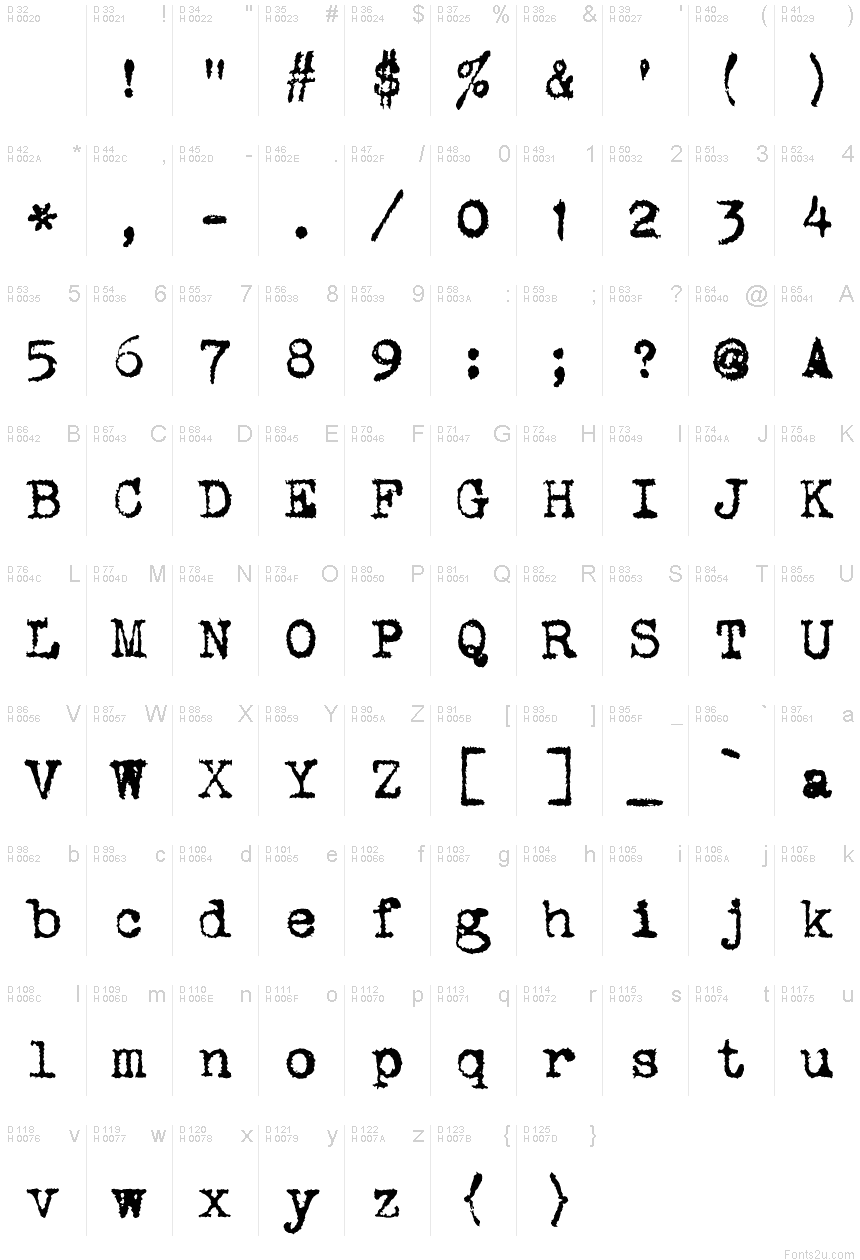
VTCorona
VT Corona, autorstwa Susan Townsend, to darmowy, surowy krój displayowy w stylu old-school, przywodzący na myśl klimat zużytych czcionek drukarskich i obitych drewnianych liter. Krawędzie znaków wyglądają na nadgryzione, a nierówne kontury i miękkie prześwity sprawiają, że projekt sprawia wrażenie autentycznie zniszczonego, a nie tylko sztucznie postarzonego.
Doskonale sprawdzi się na plakatach, nagłówkach w klimacie horroru, fanzinach, planszach tytułowych, etykietach barowych i ulotkach wydarzeń, gdzie darmowy font musi mieć charakter, ale nie może być zbyt udziwniony. Wykorzystaj go do krótkich nagłówków, logotypów lub pojedynczych słów, które zyskają dzięki tym poszarpanym konturom – faktura sama w sobie buduje nastrój, zanim dodasz cokolwiek więcej.